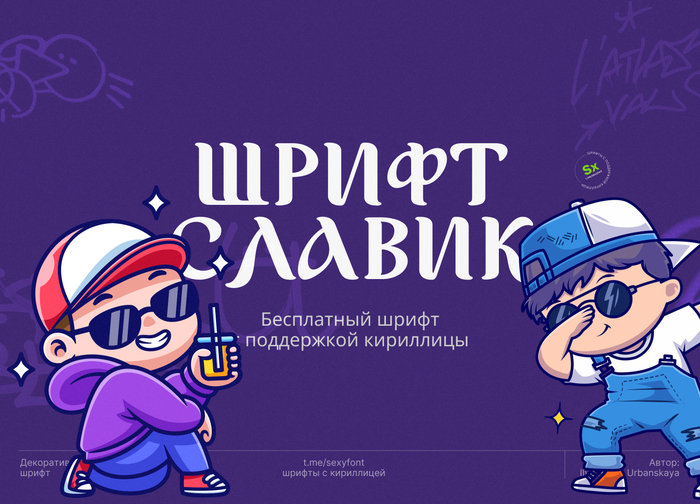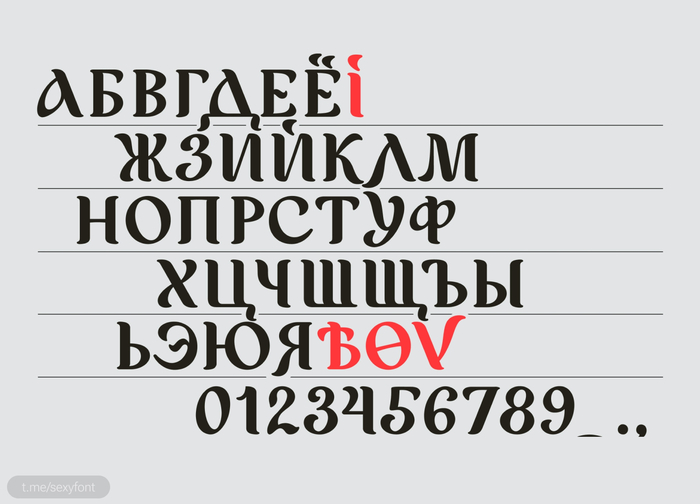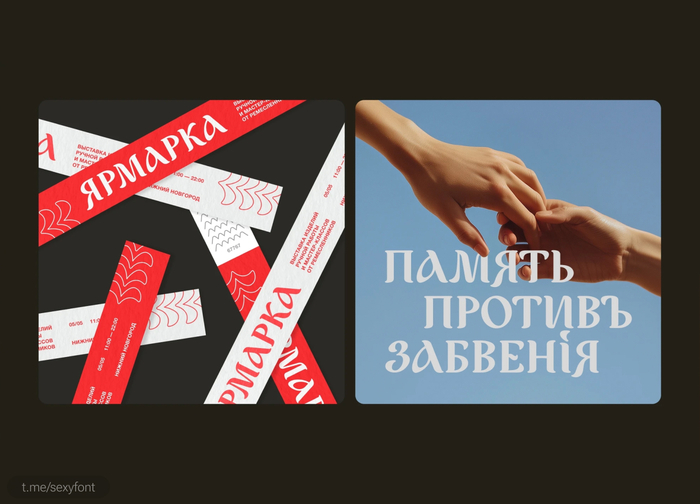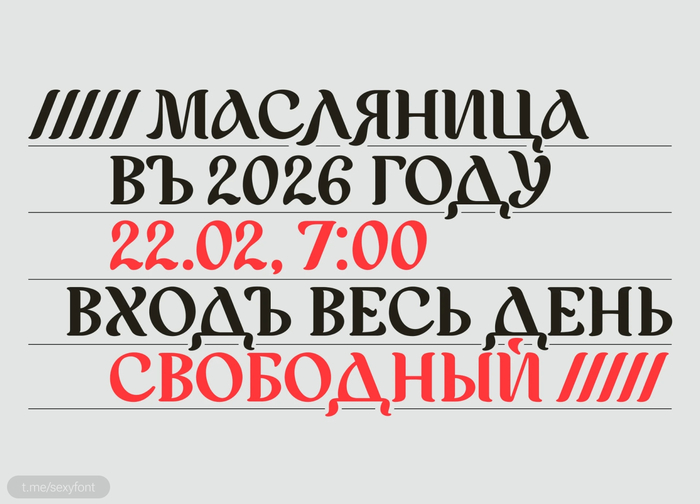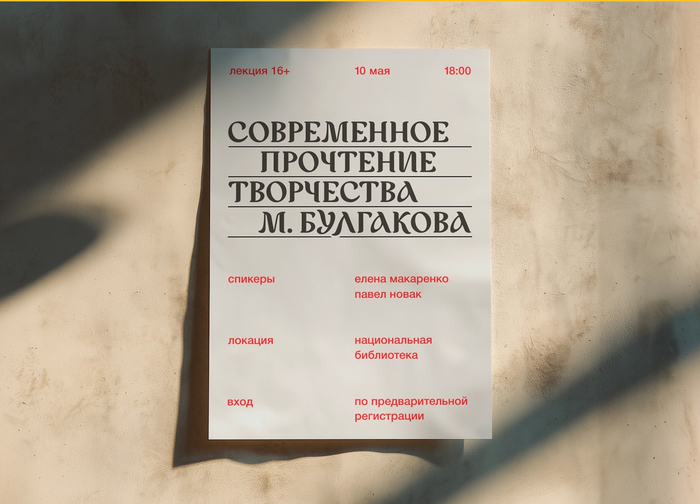
Бесплатный Шрифт Славик
Кириллический шрифт, вдохновленный дореформенной орфографией. Помимо привычных нам литер он включает в себя 4 упраздненные буквы: І (и десятеричное), Ѣ (ять), Ѳ (фита) и Ѵ (ижица).
Этот шрифт является результатом переосмысления дореформенной орфографии: он приветлив, непоседлив и отчасти дерзок. Славик демонстрирует данный архаизм в более дружелюбном ключе.